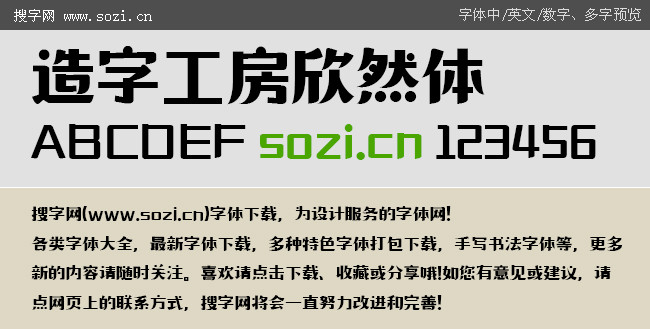
造字工房欣然體
搜字網(wǎng)給大家提供一款造字工房欣然體中文字體下載,造字工房欣然體字形承襲宋體之莊肅卻又不顯拘泥、特點(diǎn)極富變化卻無(wú)粗制造作之感,整體風(fēng)格穩(wěn)重挺拔,剛?cè)嵯酀?jì)。點(diǎn)畫和口部的匠心處理令字體風(fēng)格更富現(xiàn)代感。適用于大標(biāo)題、品牌廣告宣傳等需要強(qiáng)力視覺表現(xiàn)的環(huán)境等應(yīng)用。(本字體為個(gè)人非商用版,如需要商用請(qǐng)聯(lián)系官方購(gòu)買版權(quán))